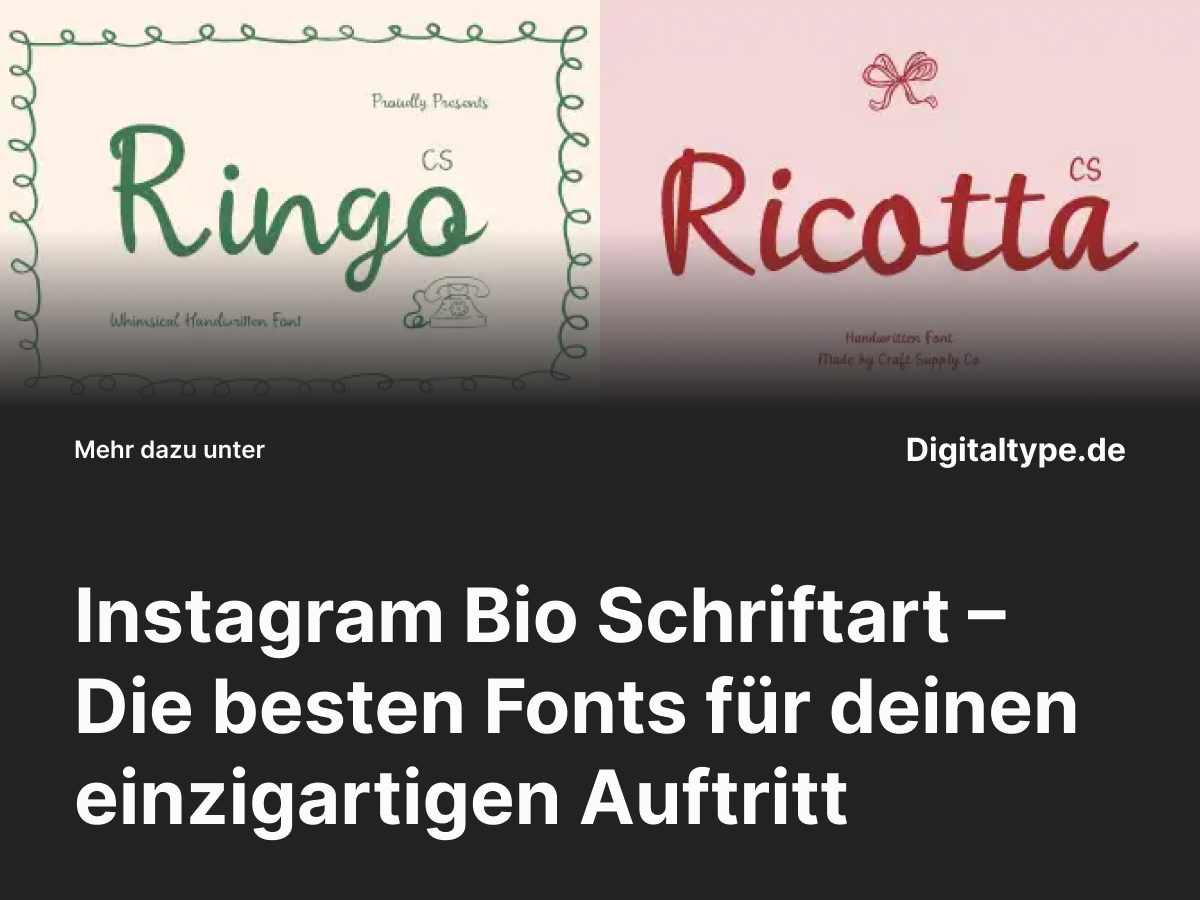
Deine Instagram-Bio ist der erste Eindruck, den Besucher von deinem Profil bekommen. Mit einer Instagram Bio Schriftart kannst du deinen Stil unterstreichen, dich abheben und deinem Profil eine persönliche Note verleihen.
In diesem Artikel stellen wir dir 6 stilvolle Script-Schriften vor, die perfekt zu kreativen, eleganten und modernen Instagram-Designs passen.
Was ist eine Instagram Bio Schriftart?
Eine Instagram Bio Schriftart ist eine Schrift, die deinem Instagram-Profil durch individuelles Design Ausdruck verleiht.
Ob elegant, verspielt oder minimalistisch – mit der richtigen Schriftart kannst du Emotionen wecken und deine Marke oder Persönlichkeit unterstreichen.
Da Instagram selbst keine direkte Schriftänderung zulässt, verwenden viele Nutzer externe Tools oder gestalten ihre Bio mit stilvollen Fonts in Grafikprogrammen, um ihren Look zu personalisieren.
Warum du eine individuelle Schriftart für deine Instagram-Bio nutzen solltest
- 1. Persönlichkeit zeigen: Deine Schriftwahl sagt viel über dich oder deine Marke aus.
- 2. Aufmerksamkeit gewinnen: Eine auffällige Schrift zieht sofort den Blick auf dein Profil.
- 3. Professionelles Erscheinungsbild: Einheitliches Branding mit passender Schrift stärkt deine visuelle Identität.
- 4. Emotionale Verbindung: Schriften wecken Gefühle – von elegant bis kreativ oder verspielt.
Mit einer passenden Instagram Bio Schriftart kannst du dein Profil individuell gestalten und deine Botschaft optisch verstärken.
Die 6 besten Instagram Bio Schriftarten für kreative Profile
Hier findest du sechs ausgewählte Instagram Bio Schriftarten, die durch Stil, Ausdruckskraft und Eleganz überzeugen. Perfekt für Bios, Social-Media-Grafiken und Branding-Designs.
1. CS Ringo Handwritten Script Font
CS Ringo ist eine lebendige Handschrift mit natürlichem Fluss. Ideal für kreative Profile, die Authentizität und Persönlichkeit betonen möchten.
2. CS Ricotta Handwritten Script Font
Eine elegante Script-Schrift mit modernen Kurven. Perfekt für Lifestyle-, Fashion- oder Künstlerprofile, die Wert auf Ästhetik legen.
3. CS Renita Script Font
Renita überzeugt mit feinen Linien und femininer Anmutung. Sie verleiht deiner Bio einen professionellen und charmanten Touch.
4. CS Greylin Script Font
Ein moderner, leicht verspielter Script-Font mit klarer Struktur. Ideal für Designer, Content-Creator oder Marken mit kreativem Anspruch.
5. CS Glinka Script Font
CS Glinka kombiniert fließende Linien mit raffinierter Typografie. Eine großartige Wahl für elegante Bios oder Branding-Designs.
6. CS Gifted Script Font
Gifted ist ein moderner Script-Font mit weichen Kurven und künstlerischem Flair. Ideal für kreative und emotionale Online-Auftritte.
Design-Tipps für Instagram Bio Schriftarten
- 1. Wähle Schriften passend zur Markenidentität: Elegant, minimal oder verspielt – je nach Stilrichtung.
- 2. Einheitliches Branding: Verwende dieselbe Schrift in Story-Highlights, Beiträgen und Reels.
- 3. Achte auf Lesbarkeit: Auch auf mobilen Geräten sollte dein Text gut erkennbar bleiben.
- 4. Kombiniere sparsam: Nutze maximal zwei Schriftarten für ein harmonisches Erscheinungsbild.
Fazit: Instagram Bio Schriftart für deinen individuellen Stil
Eine Instagram Bio Schriftart ist der Schlüssel zu einem stilvollen und wiedererkennbaren Profil.
Ob du einen modernen, eleganten oder verspielten Look bevorzugst – mit der richtigen Schrift hebst du dich von der Masse ab und hinterlässt Eindruck.
Die vorgestellten Fonts bieten dir eine inspirierende Auswahl an hochwertigen Schriften für kreative Bios und Social-Media-Auftritte.